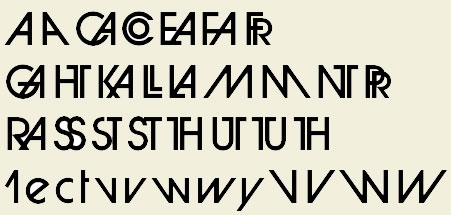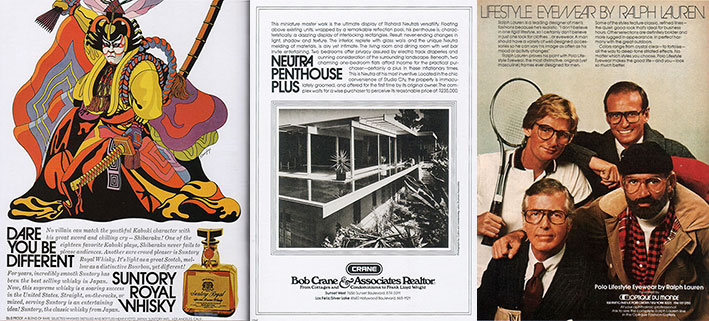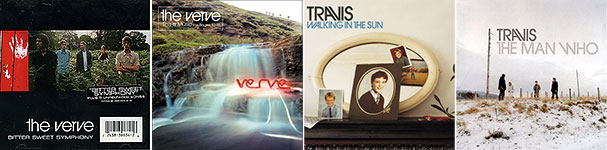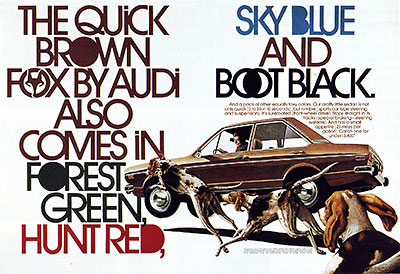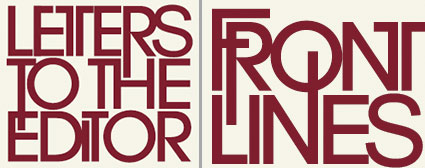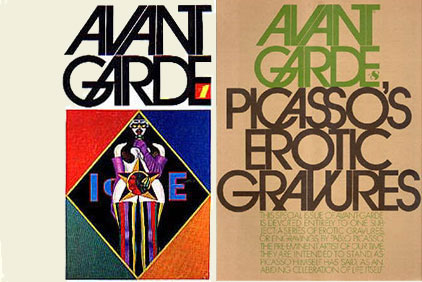
Avant Garde: die synthetische SchriftEigentlich sollte Avant Garde keine Schrift werden. Herb Lubalin
zeichnete ihre Großbuchstaben 1968 für das Logo des gleichnamigen
US-Kulturmagazins. Doch ausgebaut zum Alphabet wurde sie Anfang der 1970er Jahre
zum typografischen Pop-Star. Für den Mengensatz ist sie ungeeignet, was
Typo-Laien wenig stört. Die wahre Geschichte der Avant Garde
![]() Mitte der 60er Jahre entstand in New York die Idee für eine
Zeitschrift mit dem Titel »Avant Garde«. Es sollte »ein
intelligentes, fröhliches Kunst- und Politikmagazin werden, für Leute,
die ihrer Zeit voraus sind« (O-Ton Avant Garde Magazine).
Der Herausgeber Ralph Ginzburg und Herb Lubalin entwickelten die visuelle Sprache der Zeitschrift. »Es war eine schwierige Zusammenarbeit« erinnert sich Ginzburg. »Sein (Lubalins) erster Logo-Entwurf war in Hebräisch. Er dachte das sei lustig. Dann machte er im Coca-Cola-Stil weiter. Wir sind ein Dutzend Entwürfe durchgegangen, alle meisterhaft ausgeführt. Aber keines überzeugte uns.« ![]() Die Erstausgabe der Zeitschrift Avant Garde (1968, links) und Ausgabe 8 (1969) Eines Tages suchten Ginzburg und seine Frau Shoshana den ratlosen Herb Lubalin in seinem Büro auf. Sie erläuterten ihm noch einmal das Konzept der geplanten Publikation. »Ich bat ihn, sich einen modernen europäischen Flughafen vorzustellen.« erinnert sich Shoshana Ginzburg. »›Denke an ein Düsenflugzeug, das die Startbahn verlässt und in die Zukunft fliegt.‹ Mit meiner Hand beschrieb ich die Flugbahn als eine aufsteigende Diagonale. Er ließ mich das ein paar Mal wiederholen. Ich erklärte ihm, dass die bisherigen Logos zu vielen Magazinen passen könnten, aber Avant Garde sollte etwas bekommen, was noch niemand zuvor gesehen habe: einzigartig und völlig neu.« ![]() Der New Yorker Designer und Schriftgestalter Herbert F. Lubalin (1918 – 1981; Foto © 1979 The American Institute of Graphic Arts) Als Herb Lubalin am nächsten Morgen von seinem Wohnort Woodmere (New York) zur Arbeit fuhr, lenkte er plötzlich den Wagen an den Straßenrand. Von einer Telefonzelle aus rief er Ralph Ginzburg an, was er noch nie zuvor getan hatte: »Ralph, ich hab die Lösung. Du wirst es sehen.« Der Rest ist Designgeschichte. Lubalins Startpunkt waren Großbuchstaben der Stilrichtung Geometrische Groteskschrift (in den USA »Gothic)« genannt, irgendwas zwischen Futura und Helvetica. Er verwinkelte die beiden As und das V so, dass sie sich wie Kuchenstücke nahtlos aneinander fügten. Dabei erinnerte er sich an Shoshana Ginzburg Handbewegung. Er halbierte das T und verschmolz es mit dem N. Das dritte A im Schriftzug steht mit einem Bein im kreisrunden G, wobei sich die Horizontalen überlagern. R, D und E berührten sich, so das sich schließlich zwei kompakte Buchstabenblöcke ergaben. Sie bildeten das unverwechselbare Avant-Garde-Logo. ![]() Das Original-Avant-Garde-Logo mit der aufsteigenden A-Diagonale über zwei Zeilen (nachgebaut mit Avant Garde Book und Book Alt von E+F) Um Anzeigenkunden zu gewinnen, konzipierten Ginzburg und Lubalin eine Promo-Broschüre, in der alle Headlines in der Avant-Garde-Schrift gesetzt werden mussten – ausnahmslos Versalien. Lubalin verbrauchte drei Assistenten, um die 26 Buchstaben des Alphabets in Rekordzeit zu zeichnen. Dann schaltete sich sein Partner Tom Carnese ein, der früh erkannte, dass man ohne Buchstabenpaare kaum brauchbare Ergebnisse mit der geometrischen Schrift erzeugen könne. Mit jedem Wort, das sie zeichneten, entstanden neue Ligaturen. Irgendwann lagen genügend Zeichen vor, um das Heft fertig zu stellen: ja jetzt konnten sie sogar einen Fotosatz-Prototypen der Avant Garde bei Photo Lettering, Inc. in Auftrag geben. ![]() Promo--Broschüre für das »Avant-Garde«-Magazin: alle Buchstaben handgezeichnet, mit Versal-Ligaturen von Tom Carnese (Foto: Fontblog) ![]() Zwei handgezeichnete Kolumnen-Titel des Magazins »Avant Garde« ![]() Die essenziellen Avant-Garde-Ligaturen, wie sie heute wieder in der digitalen Version als Alternates (Hersteller: E+F)angeboten werden Trotz ihrer geringen Verbreitung sprach sich ab 1968 die Kunde einer neuen, avantgardistischen Schrift in New York herum wie ein Lauffeuer. Werber und Art-Direktoren waren heiß auf das Alphabet und wollten es ebenfalls für ihre Arbeit verwenden. Irgendwann konnte man sich bei Photo Lettering Headlines in Avant Garde setzen lassen, doch die Setzerei benutzte die Schrift ohne Genehmigung, sehr zum Unmut ihrer Entwerfer. ![]() Die Werbeindustrie flog auf die neue Schrift Avant Garde: Suntory Royal Whisky (1971), Bob Crane & Associates Realtor (1979), Ralph Lauren Polo Lifestyle Eyewear (1977) ![]() Der Fanatismus für die neue Avant Garde, gepaart mit den Möglichkeiten des Fotosatzes, ließ bei manchen Art-Direktoren die Gäule durchgehen. DDB-AD Dieter Krone kreierte die Fox-Kampagne für Audi, mit Headlines und Lesetext aus Avantgarde. Form follows Technik: ausgestanzte und sich überlappende Buchstaben ... sogar der Claim war inspiriert vom Schriftmustertext »The Quick Brown Fox ...«. Um dem Schwarzmarkt das Wasser abzugraben, erstellte Tom Carnese einen Satz Schriftmusterkarten. Mit diesen bewarb er sein Büro Lubalin Smith Carnese als die einzige autorisierte Avant-Garde-Setzerei. Bald konnten sie sich vor Aufträgen kaum mehr retten. Eine logische Folge war 1970 die Gründung der International Typeface Corporation (ITC) durch Herb Lubalin, Aaron Burns und Ed Rondthaler. Die revolutionäre Idee hinter ITC: eine Hardware-unabhängige Schriftbibliothek aufzubauen, die ihre Entwürfe an die Satzgeräte-Hersteller lizenziert. Bis dahin arbeiteten Monotype, Linotype und Co. mit proprietären Schriftentwürfen. Manchmal tauschten sie Lizenzen aus, manchmal wurde abgekupfert. ITC wollte ab sofort klare Verhältnisse beim Schutz des Urheberrechts für die Schriftentwerfer schaffen. ![]() Die berühmteste Marke, die sich der Avant-Garde-Kleinbuchstaben bediente, war adidas: Anzeige aus dem Jahr 1975 Die erste Belastungsprobe für ITC war die Schrift Avant Garde, die mit reichlich rechtlichem Gerangel auf den Markt kam. Herb Lubalin hatte zwar die Rechte für das Desig, doch Ralph Ginzburg war im Besitz die Marken- bzw. Namensrechte. Er stellte sie kostenlos zur Verfügung unter der Voraussetzung, dass der Schriftname stets mit einem Copyright-Zeichen ® gekennzeichnet sein solle. Lubalin und Burns ignorierte diese Forderung, was Ginzberg verärgerte. Er hatte aber keine finanziellen Mittel, um gegen den Warenzeichenmissbrauch zu klagen. Ganz im Gegenteil: er musste auch seine Zeitschrift bald einstellen, während die gleichnamige Schrift weltberühmt wurde. ![]() Eines der bekanntesten Cover der Schriftgeschichte: Avant-Garde-Magazin Ausgabe 13 (1970), nachgebaut mit Avant Garde Book, Book Alt, Medium und Medium Alt von E+F; Abbildung bxp57830, Retro Family, Brand X Pictures »Ich glaube, mit der Schrift haben einige richtig Geld verdient, einschließlich Herb« vermutet Ralph Ginzberg heute. »Aber Carnese, der alle Originalzeichnungen für die Light-, Demi- und Bold-Schnitte herstellte, hatte überhaupt nichts davon. Das nehme ich denen übel. So behandelt man keine Partner.« Vielleicht tröstete sich Carnese damit, dass kaum jemand in der Lage war, mit der nicht einfach zu bedienenden Schrift umzugehen. Viele beschäftigten sich nur oberflächlich mit den Ligaturen. Bei den Kleinbuchstaben berührten sich bei falscher benutzung das r und das n, so dass man unweigerlich ein m las. So ruinierten viele Avant-Garde-Benutzer ihr liebstes Kind selbst. Übrigens veröffentlichte ITC nach der phänomenalen Premiere bald eine Serifen-Version der Avant Garde, entworfen von Toni Si Spigna. Ihr Name: Lubalin Graph. ![]() Diese Anzeige bestätigt eine These des Schriftentwerfers Ed Benguiat: ... keine Schrift für Anfänger, und am besten lässt sich das Wort Avant Garde setzen Kaum eine Schrift gibt derart lupenrein einen Zeitgeist wider wie Avant Garde. Sie stammt aus der Zeit eines ungetrübten Technik-Glaubens: Die Menschheit bereitete sich gerade auf den ersten Mondbesuch vor. Die Zeitgebundenheit macht Avant Garde für heutige Kommunikationsaufgaben unbrauchbar, es sei den man gestaltet 70er-Jahre-Zitate. Trotzdem ist sie eine sehr beliebte Schrift, gerade bei Laien. Vielleicht liegt es daran, dass ungeübte Augen angesichts ihrer extremen Formen zum ersten Mal realisieren, dass es verschiedene Schriften gibt. Und von da an heißt es: »Wenn’s wie designt aussehen soll, muss Avant Garde ran.« Dabei ist die Schrift nichts für Anfänger. Ihr Einsatzgebiet ist klein, wie das der meisten konstruierten Groteskschriften. Die Idee, eine Schrift nicht vom Schreiben her wachsen zu lassen sondern zu konstruieren, stammt bereits aus den 1920er Jahren: Funktionalismus, »mechanisierte Graphik« (Paul Renner). Damals entstanden Futura, Erbar und Bernhard Gothic. Aber niemand wagte sich so weit weg von den Lesegewohnheiten wie Herb Lubalin. Für die weite Verbreitung der Avant Garde im digitalen Zeitalter, das Ende der 1980er Jahre begann, sorgte die Seitenbeschreibungssprache PostScript. Die ersten PostScript-Drucker waren unter anderem mit Avant Garde bestückt. Und da es damals nur eine Handvoll Schriften gab, musste Avant Garde stets als »ausgefallene« Alternative herhalten. Avant Garde heute: ![]() Plattencover der Bands The Verve und Travis ![]() Stanley-Kubrick-Anthologie, Taschen Verlag Zitate zu Avant Garde: Ed Benguiat: »Das einzige, wo Avant Garde gut aussieht, ist im Wort Avantgarde.« Tony Di Spigna, Partner von Lubalin: »Die meist-missbrauchte Schrift der Welt.« Alex W. White, Buchautor: »Eine Ansammlung derart extremer Formen erzeugt Müdigkeit in Textgrößen und lenkt alle Aufmerksamkeit auf sich, was bekanntermaßen die größte Sünde ist, die eine Schrift begehen kann.« Steven Heller: »Das Paisley(-Muster) unter den Schriften.« Stephen Coles, Typographica: »Mit dem Erscheinen der Alternates sind die Fluttore wieder geöffnet.« Art Chantry, Designer: »Als Anfänger habe ich an Avant Garde gelernt, wie Typografie nicht funktioniert.« Dieter Krone, Art-Director DDB: »Fotosatz mit Avant Garde bedeutete, das Buchstaben- und Zeilenabstände negative Werte annehme konnten. Und was möglich war, wurde gemacht.« Fontblog: »Avant Garde ist keine Schrift, sondern ein Retortenprodukt. Wahre Schriften werden geboren, sie leben. Konstruierte Alphabete sind totes Typo-Material«. Literaturhinweise: The Typehead Chronicles (http://webs.lanset.com/bookfolk/typehead/avant_garde.htm) Alex White on Herb Lubalin's Avant Garde (http://www.graphic-design.com/Type/Avant/Avant2.html) AIGA - Crimes Against Typography (http://journal.aiga.org/content.cfm?ContentAlias=_getfullarticle&aid=537383) Lewis Blackwell: »20th Century Type«, Laurence King Publishing, London 1992 Helmut Krone: The Book, Cambridge Enchorial Press Ltd, 2005 (Online-Version durchblättern) Herausgegeben: Di - August 30, 2005 at 01:26 nachm. | |